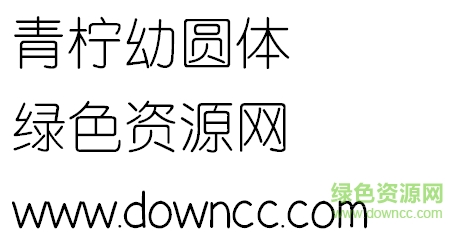
青檸幼圓體是一款非常秀氣好看的幼圓字體,簡答大方的筆觸讓你的設(shè)計更增獨(dú)特魅力,只會中英文輸入,喜歡的朋友來綠色資源網(wǎng)免費(fèi)下載吧!
青檸幼圓體有著幼圓的溫柔圓潤,也有楷體書法的大方得體,是一款不可多得的藝術(shù)字體,十分耐看,應(yīng)用于平面設(shè)計、海報設(shè)計、LOGO創(chuàng)作等將大有裨益!
幼圓字體看起來有些像微軟雅黑,但比雅黑更纖細(xì)、轉(zhuǎn)角更圓、更顯女性化,相當(dāng)可愛,居家必備!
幼圓體的主要特點(diǎn)是:
1.在舊版本的幼圓體中,對舊字形的處理比較到位。
2.拐彎處筆劃處理尤為細(xì)膩。
3.筆劃更加細(xì)長,便于閱讀。